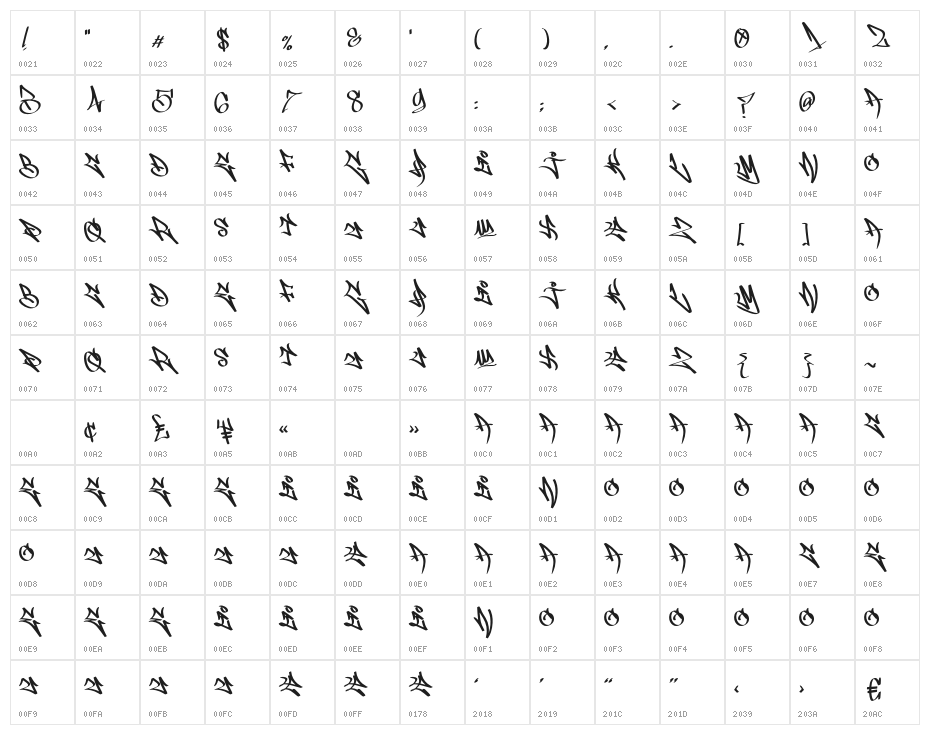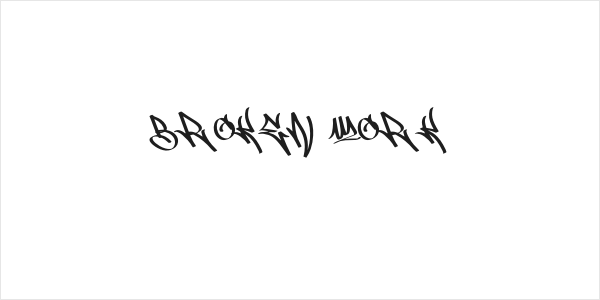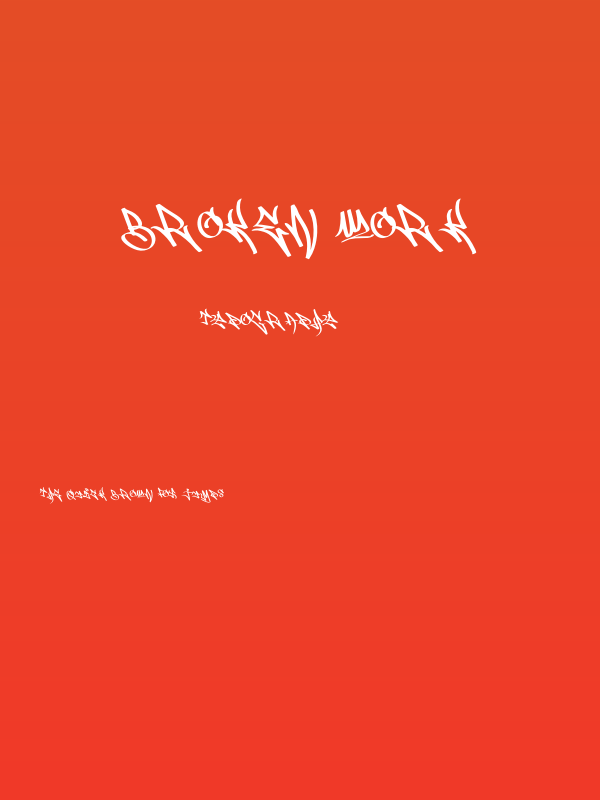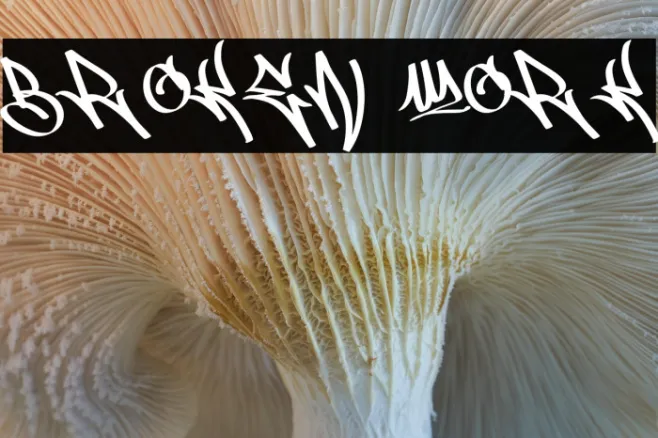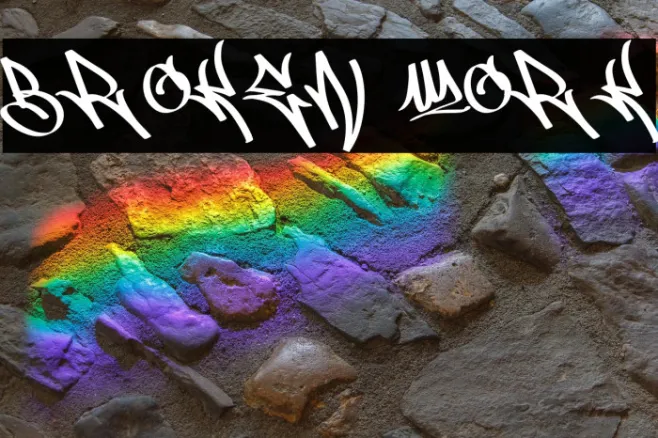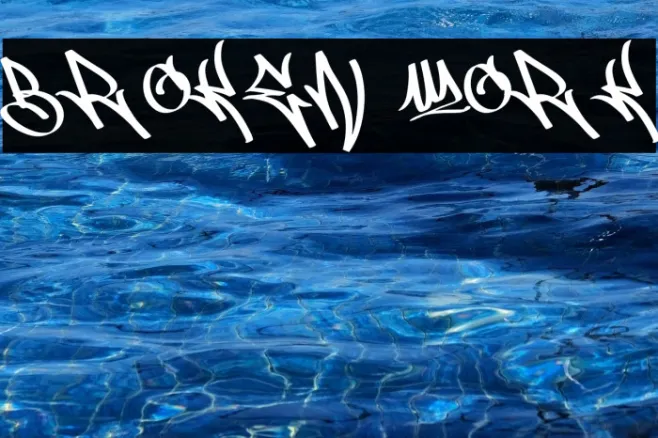
Broken Work Font
| Gesamtstil | Urban, Rebellious, Energetic |
| Anwendungsfall | Logos, Posters, Album Covers |
| Vorgeschlagene Projekte | Ideal for street art designs, urban-themed posters, music album covers, and edgy branding projects. |